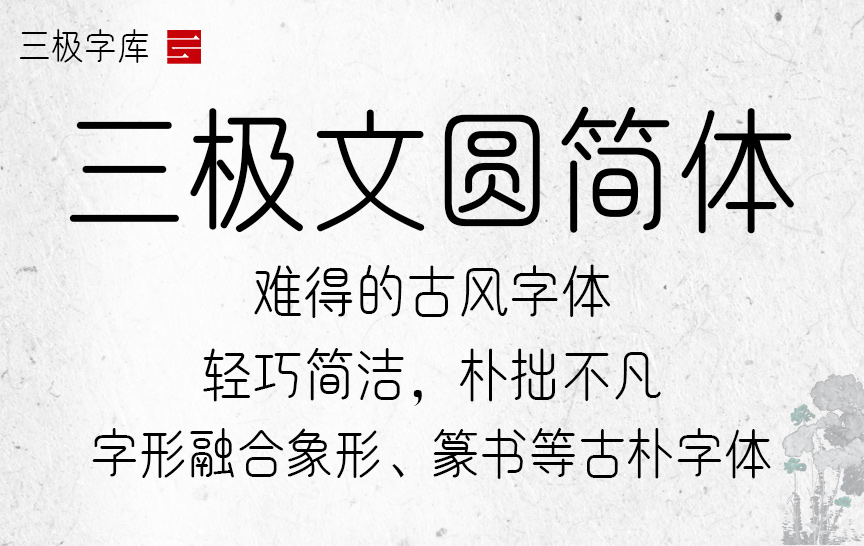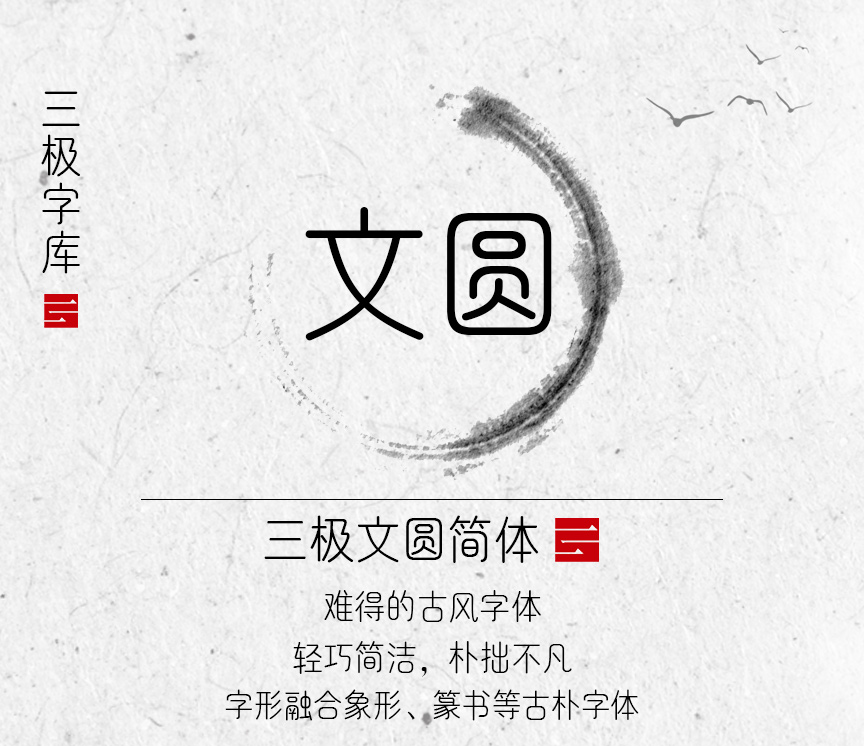
字体名称:三极文圆简体
设计师:Zhouzhou
所属分类:圆体
三极文圆简体作品整体风格独特,具有古法圆通、朴拙之感,字形融合了象形、篆书等古朴字形,使其风格简洁明快,独具一格。字体轻巧简洁,古拙而不凡。粗细匀称,起笔收笔为圆头,折、钩、撇捺转折圆润饱满,具有古拙婉转的气质。视觉效果简洁易识别,实用性强。本作品适用于传统印刷媒介的标题与正文排版,尤其适用于古典、工艺类型行业和书籍装帧。